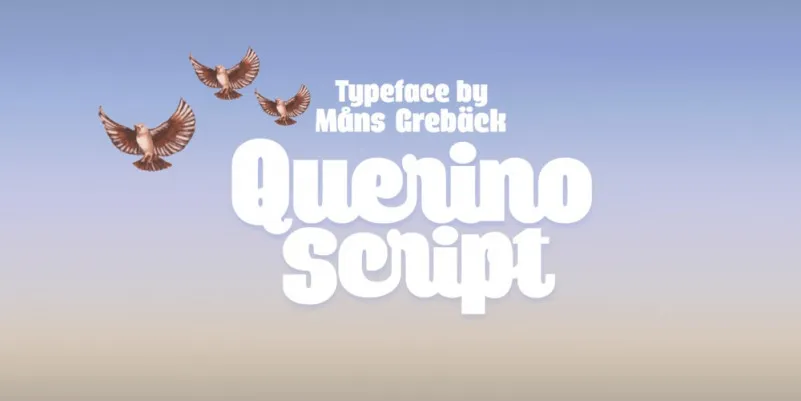
Befonts está entusiasmado ao apresentar uma nova fonte script, Querino Script Font. Esta elegante tipografia bold é inspirada em tipos clássicos associados a marcas de luxo, beleza e curvas elegantes. Suas contraste alto e sua sensação geralmente envolvente fazem dela uma escolha perfeita para projetos artísticos e tipografia em todas as plataformas. Querino Script Font é um extra-bold serif font criado por Mans Greback, que tem versões tanto normais quanto itálicas. Também vale a pena ver seu parceiro de irmão Querino Sans. A fonte é multilinguista e possui uma ampla gama de caracteres; ela apoia todas as línguas baseadas em alfabeto latino da Europa, incluindo números e todos os símbolos e caracteres que você possivelmente precisará.